От клинописи к алфавиту: как менялись системы письма
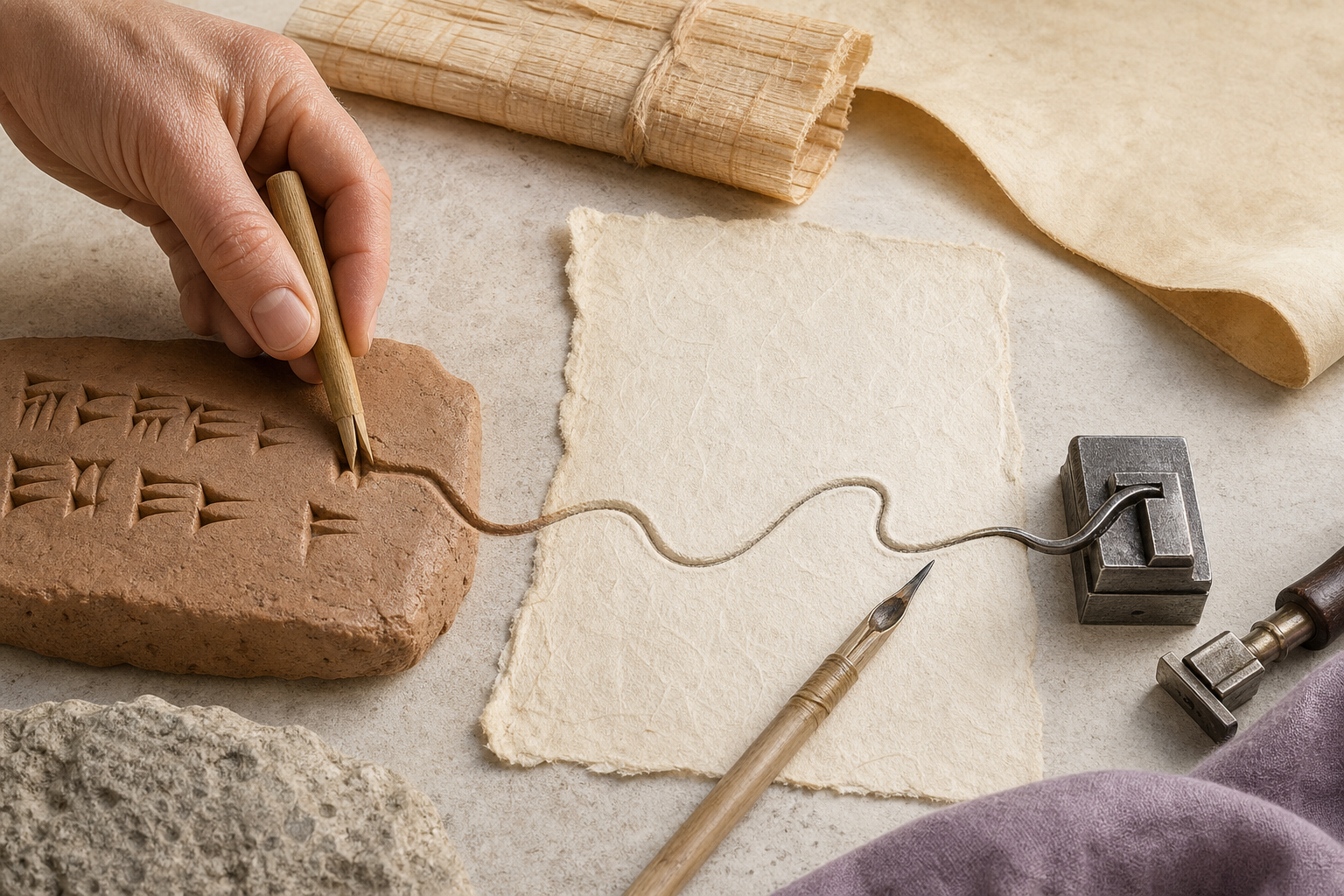
Системы письма развивались от простых изображений и знаков для учёта товаров к сложным наборам символов, способным передавать слова, слоги и отдельные звуки. Клинопись стала важным шагом к абстрактной записи речи, а алфавит упростил обучение и распространение грамотности. Ниже разберём основные этапы этой эволюции и их значение для типографики.
Письмо — это не просто набор символов, а система правил, которая связывает визуальные знаки с языком. Один знак может обозначать предмет, целое слово, слог или звук. Поэтому история письменности показывает не линейную замену «старых» знаков «новыми», а постепенное изменение задачи: от фиксации конкретных объектов к передаче всё более точной и гибкой речи.
Что такое система письма
Система письма — это организованный способ записывать язык с помощью графических знаков. Она включает состав символов, направление письма, правила соединения знаков и принципы чтения. Важно отличать письменность от языка: один язык может использовать разные системы письма, а одна графическая традиция способна адаптироваться к нескольким языкам.
По принципу передачи речи системы письма обычно делят на несколько типов. Логографические знаки передают слова или значимые части слов, слоговые обозначают слоги, а алфавитные соответствуют отдельным фонемам или близким к ним звукам. На практике многие древние письменности были смешанными и объединяли сразу несколько принципов.
- Логографическое письмо связывает знак со словом или понятием.
- Слоговое письмо использует знаки для сочетаний согласного и гласного или отдельных слогов.
- Консонантное письмо преимущественно передаёт согласные звуки.
- Алфавитное письмо стремится обозначать и согласные, и гласные.
- Смешанная система сочетает смысловые, слоговые и звуковые знаки.
До письма: изображения, метки и счётные знаки
До появления полноценной письменности люди использовали изображения, зарубки, узелки и предметные метки. Такие способы помогали обозначить количество животных, принадлежность вещи или факт обмена, но не позволяли точно записать грамматику и произношение фразы. Изображение быка могло означать животное, однако не передавало само слово в любом контексте.
Переход к письму произошёл тогда, когда знаки начали использовать не только для изображения предметов, но и для фиксации слов и звуков. Один и тот же символ мог получить переносное значение или использоваться по принципу ребуса: изображение предмета связывалось со звучанием его названия. Этот механизм стал основой для дальнейшей фонетизации письменности.
Клинопись: как знаки стали абстрактными
Клинопись сформировалась в Месопотамии как практический инструмент административного учёта. Знаки наносили на влажные глиняные таблички заострённым концом тростникового стилуса. След от инструмента имел форму клина, поэтому первоначально образные знаки постепенно превратились в набор угловатых отпечатков, удобных для быстрого нанесения на глину.
Ранние записи связывают с учётом зерна, скота, работников и поставок. Со временем клинопись стала использоваться для договоров, законов, писем, мифов и учебных текстов. В ней сочетались словесные и слоговые значения, а один знак мог читаться по-разному в зависимости от контекста. Это делало систему мощной, но требовало длительного обучения писцов.
Как читали клинописные тексты
Чтение клинописи зависело от языка, периода и жанра текста. Писец должен был знать не только форму знаков, но и традиционные значения, варианты произношения и порядок слов. Для уточнения смысла применялись специальные определители — знаки, которые подсказывали, относится ли слово к человеку, божеству, месту или предмету.
Иероглифические системы: знак, слово и звук
Египетские иероглифы демонстрируют другой путь развития письма. Их знаки могли обозначать предметы, слова, отдельные согласные или сочетания согласных. Дополнительные смысловые указатели помогали понять значение знака в конкретном слове. Поэтому иероглифическая запись не сводилась к простому набору картинок: она имела сложную фонетическую и грамматическую структуру.
Важную роль играла форма носителя. Для монументальных надписей подходили тщательно вырезанные изображения, а для повседневной работы применялись более быстрые курсивные варианты. Один и тот же язык мог существовать в нескольких графических формах, различавшихся степенью детализации, скоростью письма и сферой применения.
Похожий принцип смешения смысловых и звуковых знаков встречается и в других традициях. Китайская письменность, например, использует иероглифы, которые связывают значение со звучанием и исторически складывавшимися компонентами. Такие системы могут быть устойчивыми на протяжении веков, потому что письменный знак способен объединять носителей разных диалектов.
От слоговых знаков к алфавиту
Слоговое письмо занимает промежуточное положение между логографией и алфавитом. В нём один символ передаёт слог, например сочетание согласного и гласного. Такая система проще набора знаков для отдельных слов, но всё ещё требует большого количества символов, особенно если язык содержит много слогов или сложную морфологию.
Алфавитная идея стала особенно эффективной благодаря сокращению набора знаков. В ранних семитских алфавитах преимущественно записывали согласные. Финикийская письменность распространилась по торговым путям Средиземноморья, а греческая традиция стала важным этапом, поскольку в ней появились отдельные обозначения для гласных. Позднее через этрусскую и римскую традиции сформировался латинский алфавит.
Почему алфавит оказался удобным
Преимущество алфавита заключается не в универсальной простоте, а в экономии комбинаций. Ограниченный набор знаков позволяет записывать большое количество слов, включая новые имена и термины. Но алфавит не отменяет сложностей: языки различаются звуковым составом, орфографией, длиной слов и правилами чтения.
- Сокращает объём базового набора символов.
- Позволяет передавать незнакомые слова по звуковому принципу.
- Упрощает создание печатных шрифтов и клавиатурных раскладок.
- Поддерживает запись новых терминов и заимствований.
- Требует орфографических правил, чтобы одинаково записывать речь.
Как материалы и инструменты меняли графику
Историю письма невозможно отделить от истории материалов. Глина благоприятствовала коротким клиновидным отпечаткам, папирус — плавным линиям кисти или тростникового пера, камень — монументальным формам, а пергамент позволил развивать рукописную книжную культуру. Инструмент определял толщину штриха, ритм букв, соединения и даже направление движения руки.
Переход от рукописного текста к печати изменил не только скорость копирования, но и отношение к форме знака. Для металлических литер требовались устойчивые контуры, повторяемые размеры и согласованная система пропорций. Так постепенно укрепились понятия гарнитуры, начертания, кегля, интерлиньяжа и знакового набора, которыми пользуется современная типографика.
Чему эволюция письма учит дизайнера шрифтов
История письменности показывает, что хороший знак должен быть узнаваемым, воспроизводимым и уместным в конкретной среде. Клинопись была эффективна на глине, рукописный шрифт — на волокнистом материале, а экранный шрифт требует ясности при разных размерах. Поэтому дизайн шрифта начинается не с украшения букв, а с определения задачи, носителя и сценария чтения.
Практический пример для современного проекта
Представим шрифт для музея древней истории. Прямое копирование клинописных клиньев в каждом символе сделает текст декоративным, но может ухудшить читаемость. Более точное решение — взять исторический принцип за основу: использовать угловатые окончания, сдержанный ритм и контраст штрихов, сохранив привычную структуру современных букв.
- Определите назначение шрифта: заголовки, длинный текст, интерфейс или декоративная айдентика.
- Выберите исторический источник вдохновения, не смешивая несовместимые эпохи без причины.
- Соберите базовый набор букв, цифр, знаков препинания и специальных символов.
- Проверьте ритм слов, интервалы и читаемость на реальных примерах текста.
- Сравните шрифт в крупном заголовке, короткой подписи и небольшом абзаце.
- Скорректируйте детали после проверки на разных носителях и размерах.
Чеклист анализа любой системы письма
Чеклист помогает рассматривать письменность не только как исторический объект, но и как графическую систему. Его можно применять при подготовке лекции, исследовании культурного наследия или разработке шрифта с историческим характером.
- Определите, что обозначает знак: слово, слог, звук или смысловой класс.
- Проверьте направление письма и порядок расположения символов.
- Изучите материал и инструмент, для которых создавалась графика.
- Отметьте повторяющиеся элементы: оси, диагонали, петли, засечки и окончания.
- Сравните официальную, книжную и повседневную формы письма.
- Проверьте, какие знаки используются для чисел, пауз и грамматических уточнений.
- Отделите исторически подтверждённые особенности от современной стилизации.
Частые ошибки при изучении истории письменности
Ошибки возникают, когда современные представления о буквах переносят на древние культуры без поправки на их язык и технологию. Исторический знак нельзя оценивать только по внешнему сходству с современным символом: важно понимать, какую функцию он выполнял в конкретной системе письма.
- Считать любую древнюю картинку полноценной буквой.
- Называть все древние знаки иероглифами, игнорируя различия между системами.
- Представлять развитие письма как прямую линию от рисунка к алфавиту.
- Забывать, что один знак мог иметь несколько значений и вариантов чтения.
- Копировать декоративные символы без проверки их культурного контекста.
- Путать язык, письменность, алфавит и конкретный шрифт.
- Оценивать историческую графику только по удобству набора на современной клавиатуре.
Какая система письма считается самой древней?
Самой ранней из известных полноценных систем письма обычно называют шумерскую клинопись, возникшую в Месопотамии в конце IV тысячелетия до нашей эры. Её ранние тексты были связаны прежде всего с хозяйственным учётом, а позднее система стала использоваться для законов, литературы и переписки.
Клинопись была алфавитом?
Нет, клинопись не была алфавитом. Она объединяла словесные и слоговые знаки, поэтому один символ мог обозначать слово, часть слова или слог. Кроме того, чтение зависело от языка и контекста, что отличает клинопись от систем, построенных преимущественно на обозначении отдельных звуков.
Чем иероглифы отличаются от букв?
Иероглиф — это графический знак определённой письменной традиции, а буква — элемент алфавита, обычно связанный с отдельным звуком или фонемой. Иероглиф может передавать слово, слог, звук или смысловую подсказку, поэтому эти понятия нельзя считать взаимозаменяемыми.
Почему в алфавитах появились гласные буквы?
Отдельные гласные обозначения сделали запись произношения точнее для языков, где гласные важны для различения слов и грамматических форм. В греческой письменной традиции часть знаков, ранее связанных с согласными, получила новое применение для гласных звуков. Это стало одним из важных этапов развития алфавитного письма.
Как материал влияет на дизайн шрифта?
Материал определяет доступные движения и характер штриха. На глине удобны вдавленные углы, на камне — устойчивые вырезанные контуры, а перо создаёт перепады толщины и плавные соединения. При разработке шрифта важно учитывать, должен ли он сохранять след конкретного инструмента или только передавать настроение исторической графики.
Можно ли использовать древние мотивы в современном шрифте?
Да, но исторический мотив следует адаптировать к задаче и уважительно отнестись к его происхождению. Для заголовочного шрифта допустима выразительная стилизация, а для основного текста важнее ясность букв, интервалы и поддержка нужного языка. Хороший результат сохраняет узнаваемый характер источника, не превращая текст в набор случайных орнаментов.
Эволюция письма прошла путь от предметных меток и образных знаков к смешанным системам, слоговым обозначениям и алфавитам. На этот процесс влияли не только особенности языка, но и материал, инструмент, скорость записи, обучение и назначение текста. Для дизайнера шрифтов это напоминание: форма символа всегда связана с функцией и средой.